美術字设计技巧,你N种 “美術字”的设计方法
在字体的范畴中,有一类被称作“美术字”的字形,也有人称他们为“老字体”,这类字型大部分都是出现在建国初期,直至电脑出现后才逐渐消失,在大陆已经很少能见到它们了,它们很多都躺在书籍里。导致现在很多对字体感兴趣的朋友都不了解它们。
那我这次文章的内容,就是整理出一些简单易用的美术字型的基本笔画,借助字库字体的基本结构骨架的辅助下,通过更换笔画形态的方式,来实现N款美术字。
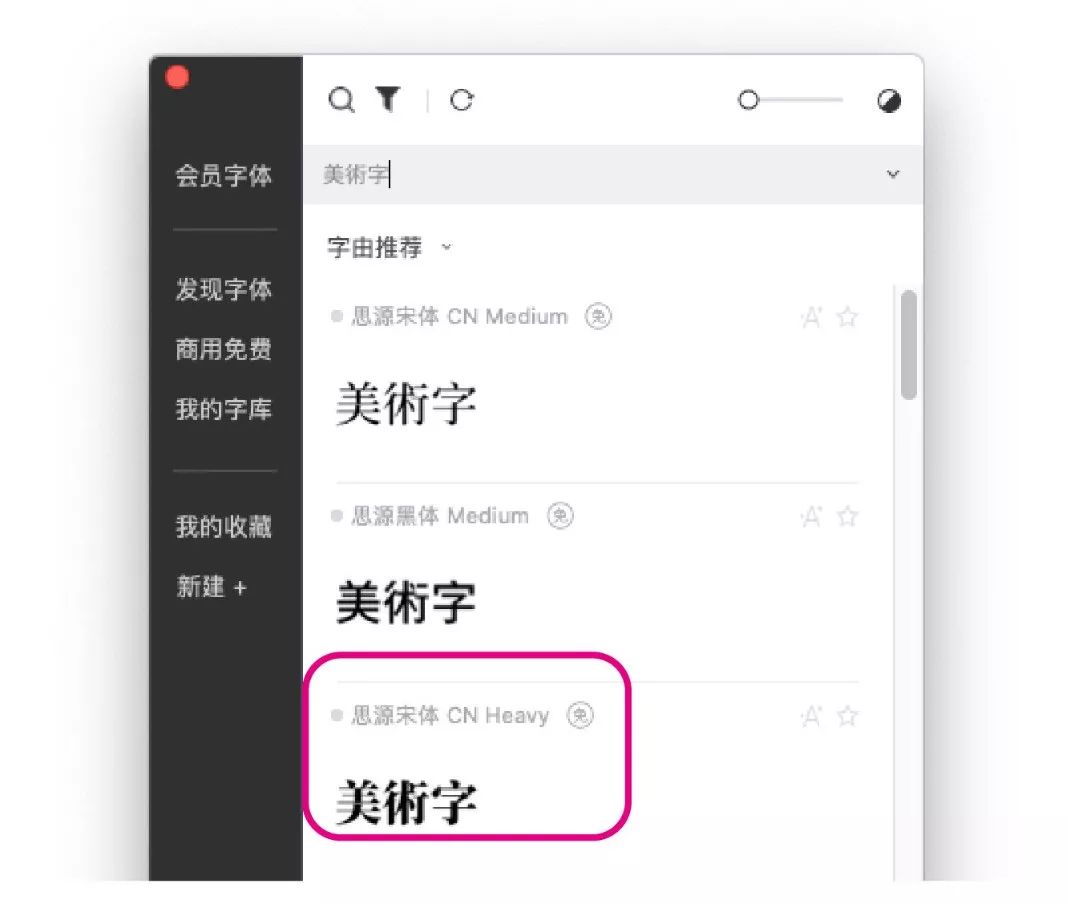
左:思源宋体 右:汉仪长美黑繁体
我们可以观察到,美术字与宋体字中撇、捺、点等曲线对比还是很相似的,只是横画加粗了,并取消了三角装饰,我们可以把它理解为是宋体与黑体二者结合的产物。这一要点理解后,开始制作基本结构。
我使用矩形工具与钢笔工具,参考宋体字的基本结构,并将横画增宽,这样美术字的基本结构就制作完成。
接下来我们就以“美術字”为案例文本,在相同的结构下展示多样的美术字。
我将每类通过颜色进行区别并进行编号,这样方面大家快速查找与运用。
共整理出18种横画形态,直接替换即可。
竖画相对少了些,共计7种竖画形态,也是直接替换即可。
撇、捺等曲线类笔画,尽可能整理的全面些,这些笔画已经可以做出大部分字了,不只限于“美術字”这三个字,这类总计有18组,这里在替换时要注意曲线的流畅度与弹性。
以上三类基本笔画,可进行随机搭配,即可实现多种字形。(以下列举几组)
还可以对笔画的粗细进行调整,这样字形就呈现出了另一种面貌。
在此基础上也可做一些简单的形变,例如拉长、压缩、倾斜……
如此这般,18种横画形态、7种竖画形态、18种撇捺曲线类笔画形态自由组合,再加上粗细字重的调整,再加上形变,保守估计“N”种字形是完全可以实现的!
最后附赠10种特异类型的“美術字”
这里注意特异类型,不能进行随机组合!!
写这篇文章的主要是帮助初学者了解美術字这类字形,尽可能做到简单易用,但由于与宋体相关,所以包含一些曲线类的笔画,对钢笔工具的使用熟练度有一点要求。其次是提供一些笔画特征,尽可能包含所有的笔画,从而辅助大家能够做出一组不错的字体。
美術字它其实并不老气,我总结的这些只能算得上是冰山的一小小角,希望对大家有所启发与帮助!